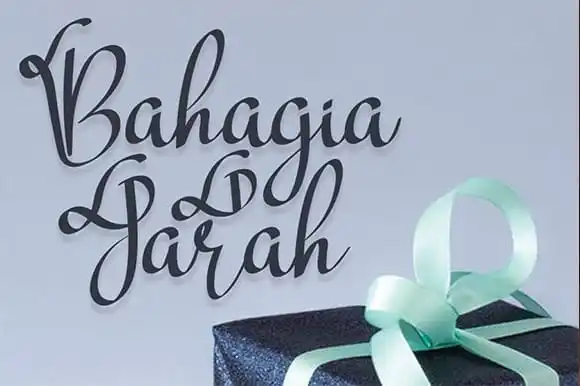
Bahagia Jarah Script Font – Fonte Grátis
Bahagia Jarah Script Font
A Bahagia Jarah Script Font é uma nova tendência em linhas de escrita perfeita para diversos projetos que exigem a elegância do traço humano. Seja para adicionar um toque único às postagens nas redes sociais, como logos ou logotipos de produtos, gráficos de marcas ou embalagens, este estilo de letra é uma opção ideal. Suas linhas arredondadas e delicadas se destacam em diferentes ambientes, desde as grandes paredes decorativas até os pequenos detalhes nas etiquetas das embalagens de produto. A Bahagia Jarah Script Font também destaca-se como uma ótima escolha para invitações de casamento ou eventos sociais, e pode ser facilmente integrada ao design dos envelopes de convite, o que a torna um recurso indispensável para qualquer projeto exigindo um traço elegante. Com sua versatilidade e beleza única, esta fonte é uma escolha perfeita tanto para aqueles procurando por algo novo no mundo da tipografia quanto para os designers em busca de inspiração para seus projetos criativos.